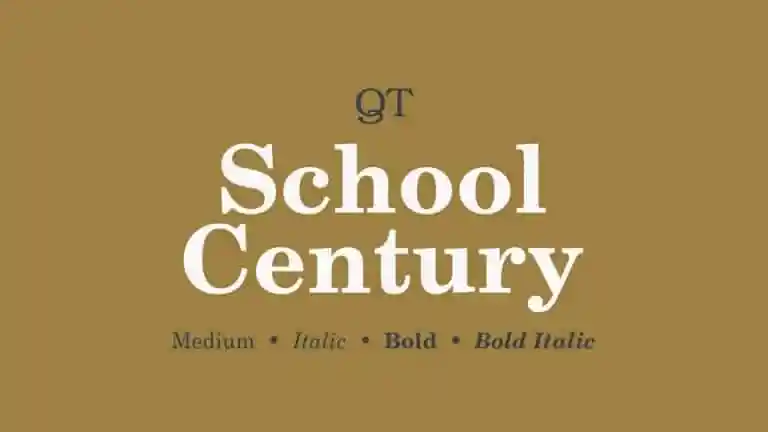
A School Century Serif Font oferece uma ampla gama de caracteres maiúsculos e minúsculos, ligaduras, figuras antiga e moderna, além dos símbolos monetários. Esta fonte é uma família de serif que vem em dois pesos com itálicas correspondentes. A família surgiu da primeira versão de um design chamado Century Roman, criado pelo designer ATF Linn Boyd Benton em 1894 para uso na The Century Magazine. Com sua tipografia serif clássica e elegante, a School Century Serif Font é perfeita para ambientes educacionais ou publicações que valorizam uma aparência formal e sofisticada. Seja para manuais escolares, revistas acadêmicas ou outros materiais de aprendizado, esta fonte será um item imprescindível na sua coleção de fontes. Seu design versátil e seu suporte latino amplo garantirão que essa família de fonts seja uma ótima opção para designers em todas as etapas do processo criativo.